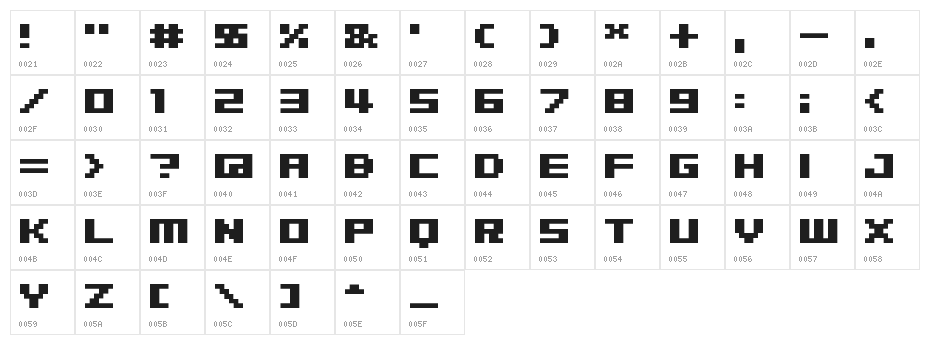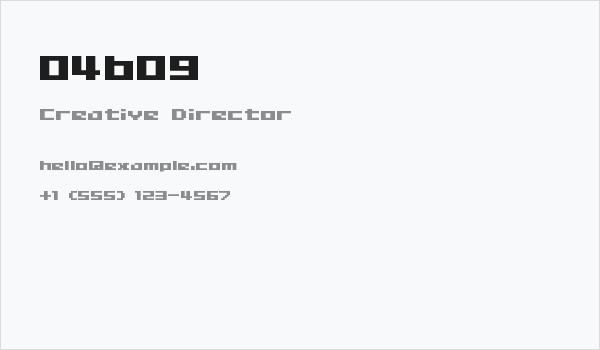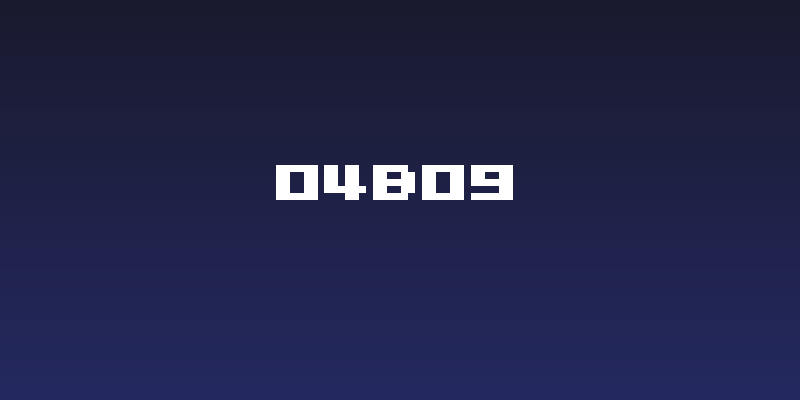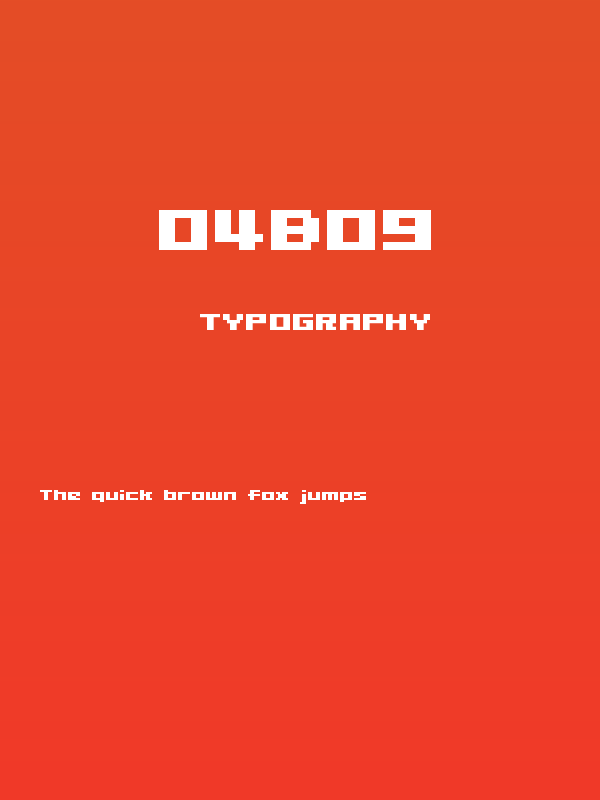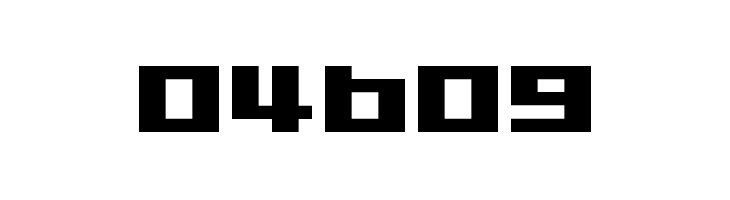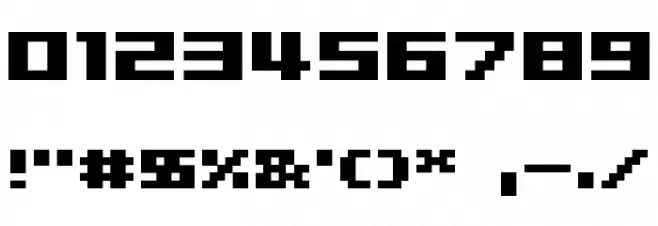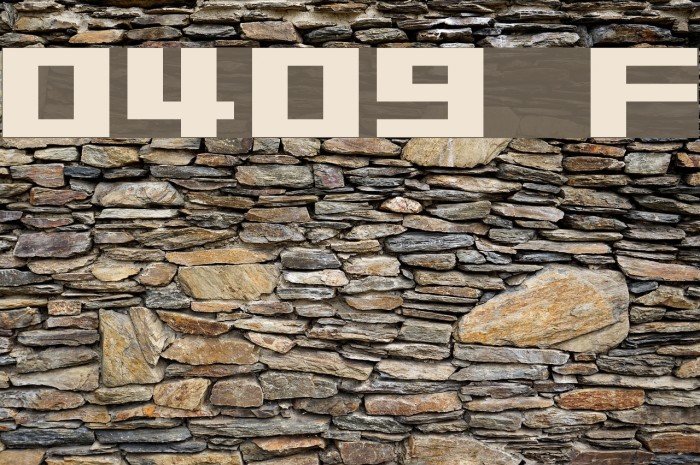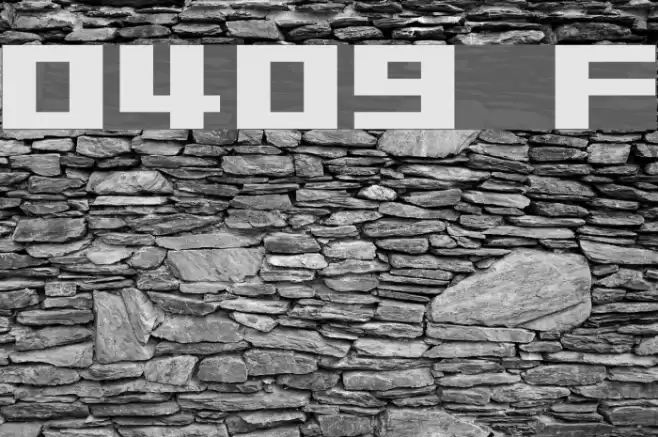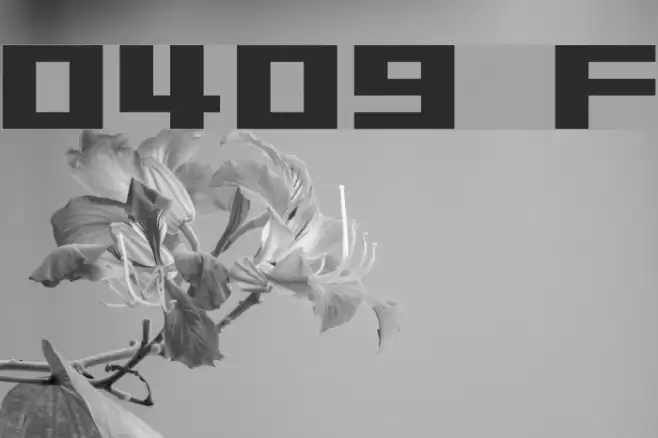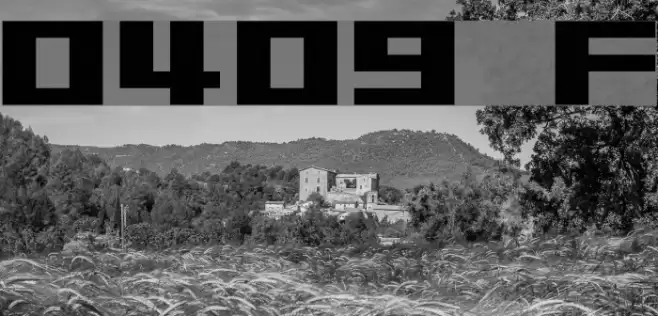
04b09 Font
| Gesamtstil | Retro, Digital |
| Anwendungsfall | Headlines, Logos, Digital Art |
| Vorgeschlagene Projekte | Ideal for video game design, retro-themed posters, digital art projects, and tech-related branding. |